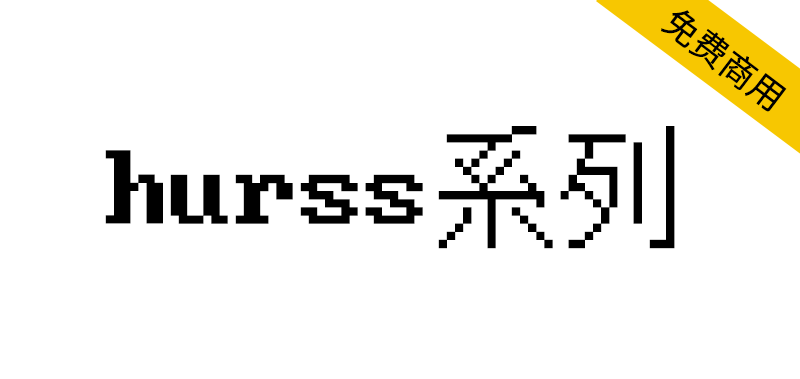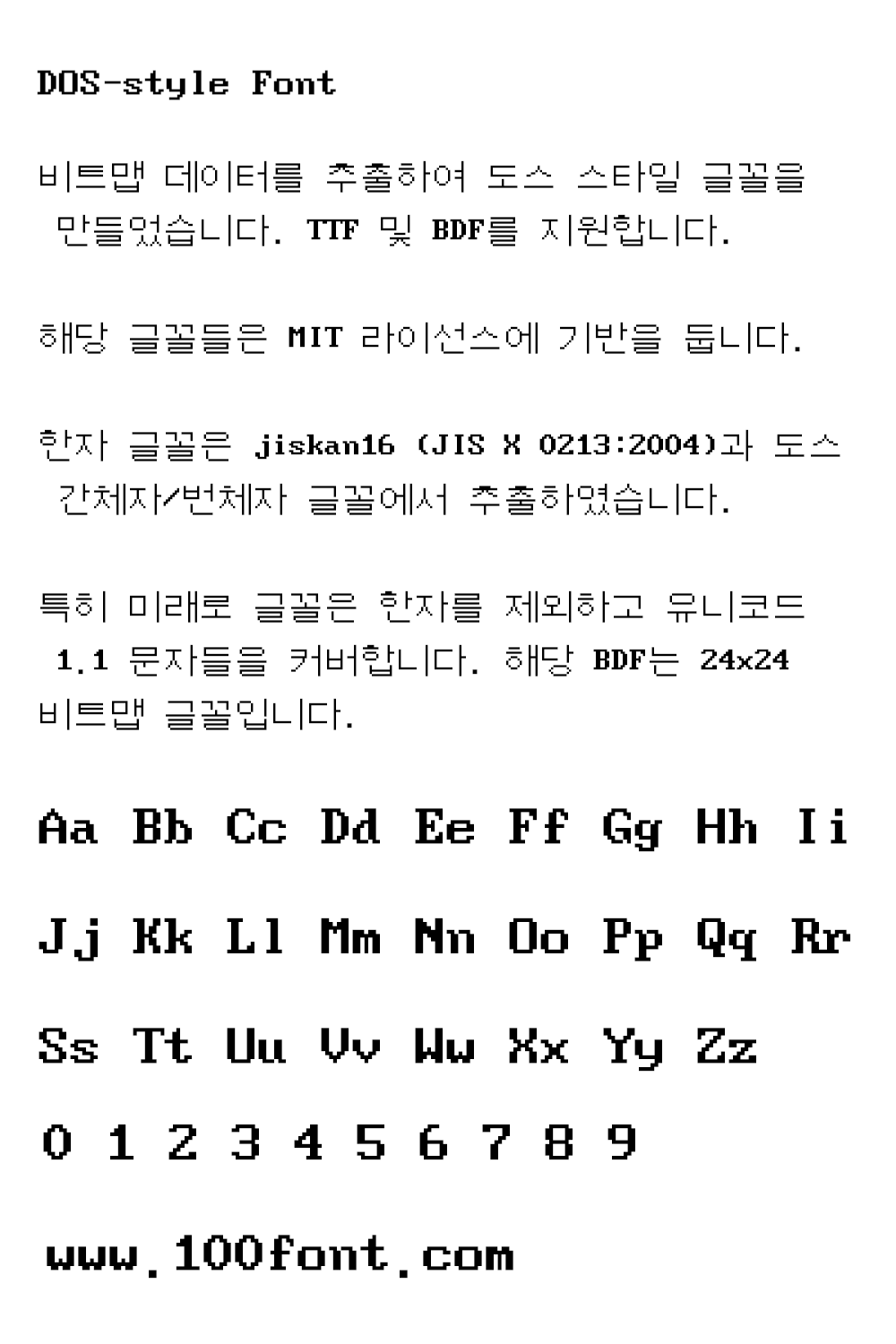
hurss系列像素字体是由韩国的Damheo Lee用位图二进制数据创建的一系列DOS风格像素字体,采用The MIT License(麻省理工学院许可证)发布,这套字体有TTF和BDF两种格式,TTF格式可以在Windows系统中使用,BDF格式可以在Linux终端中使用。
CJK表意文字是从Hanme-hangul(KS X 1001 Hanja;DOS中的一种hangul输入法)和jiskan16输入的(https://ja.wikipedia.org/wiki/Jiskan)(JIS X 0213:2004汉字);由日本电子和信息技术产业协会的Imamura和Hanataka设计。尽管如此,我们仍需要解决一些小问题。
特别是,Miraero Normal字体只包含Unicode 1.1字形,不包含CJK表意文字。它的BDF是24×24位图字体。
这套字体有几种字体样式如下:
DOSMyungjo (도스명조)
DOSGothic (도스고딕)
DOSSaemmul (도스샘물)
Sam3KRFont (삼국지3글꼴) – 한자 없음 (Not contains Hanja), MS워드 사용시 자간 뭉개질 수 있음
MiraeroNormal (미래로 글꼴) – KS X 1001 & KS X 1002 한자 (KS X 1001 & KS X 1002 Hanja), Unicode 1.1 glyphs and Euro Sign Support
DOSIyagiBoldface (도스이야기) – 이야기 굵은체
DOSPilgi (도스필기)